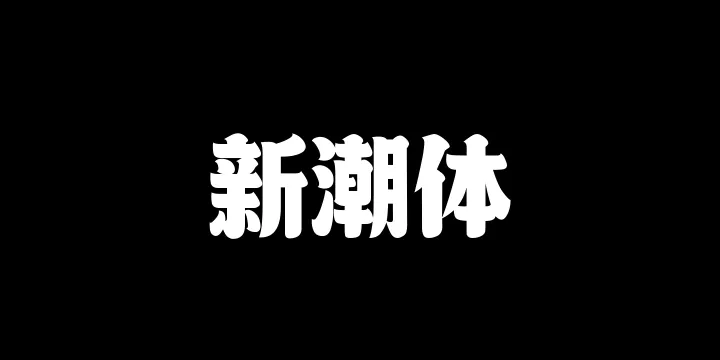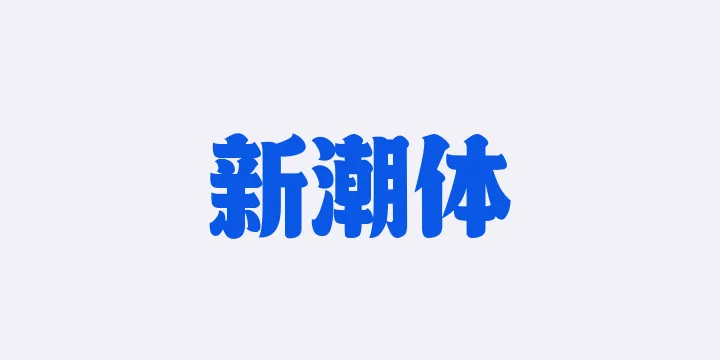
山海新潮体W By 山海字库 商用字体
字体全名: 山海新潮体W
字体简介: 山海新潮体,包含简繁汉字9169个。该字体狂野有力,非常醒目!字形规整浑厚,在浑厚的同时而又极富张力,桀骜不驯的特性,霸气外露。它的笔画充满力量感,组合搭配极富强烈的节奏感。在粗细的纵横间,拥有非常规的张力特性。
所属分类: 宋体